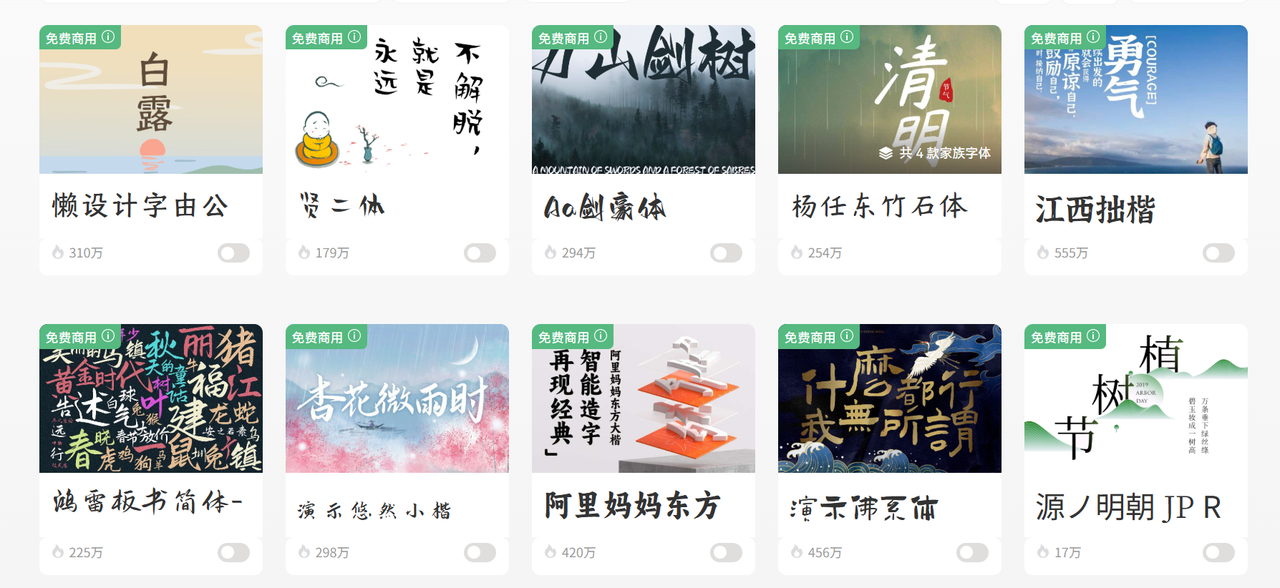
免费商用的古风字体下载网站推荐:6个靠谱平台实测分享(2026)
字由:我最常用的字体管理工具
字由 是我电脑上必装的软件,不仅仅是个下载平台,更是个字体管理神器。
在字由的字体库里,我筛选"免费商用"标签,能看到不少古风字体。比如Aa剑豪体、江西拙楷、贤二体这些,都是可以免费商用的。字由会在字体详情页清楚标注授权范围,哪些场景可以用,哪些不行,都写得很明白。
我在字由里收藏了十几款古风字体,做项目时直接搜索关键词"书法""古风""楷体",预览效果后激活使用。字由还支持字体对比功能,可以同时预览多款字体在同一段文字上的效果,选择起来特别直观。
猫啃网
猫啃网是我发现的一个专注免费商用字体的分享站。站长把网上能找到的免费商用字体都整理了出来,分类很清楚,有专门的"书法字体"栏目。
我在猫啃网下载过江西拙楷、霞鹜文楷、汉仪文黑这些字体,都是完全免费商用的。网站对每款字体都附上了授权说明链接,可以追溯到官方声明,用起来很安心。
猫啃网的界面比较朴素,没有太多花哨功能,但胜在资源全、更新快。如果你想一次性找到很多免费古风字体,这里是个好去处。有些字体在其他平台不好找,猫啃网都给整理好了。
100font
100font 主打的是精品免费商用字体收集。网站设计得比较清爽,字体数量不算特别多,但每一款都是精选过的。
我在这里找到了文泉驿正黑、思源宋体、装甲明朝等字体。其中思源宋体是 Adobe 和 Google 联合开发的开源字体,字重选择丰富,从细到粗有七个级别,用在古风设计里做标题或正文都很合适。
字体天下
字体天下 是个老牌字体下载站,资源库非常庞大。不过要注意,这里不是所有字体都免费商用,一定要筛选"免费字体"分类。
站酷字库
站酷是设计师社区,他们推出了几款完全开源免费商用的字体,包括站酷高端黑、站酷快乐体、站酷文艺体、站酷小薇logo体等。
虽然站酷的字体数量不多,但质量都不错。其中站酷快乐体带点手写感,用在一些轻松活泼的中国风设计里挺合适的。我之前做过一个新年海报,用站酷快乐体写"福"字,感觉比严肃的楷书多了点亲和力。
Google Fonts
Google Fonts 是国际知名的开源字体平台。对于中文古风字体来说,这里最值得关注的是思源字体系列(Noto 系列和 Source Han 系列)。
思源宋体是我做古风设计时的常客。它有简体中文、繁体中文、日文、韩文多个版本,笔画设计兼顾传统宋体的特点和现代阅读需求,用在书籍排版、文章配图、海报标题都很合适。
写在最后
免费商用的古风字体资源虽然不如收费字体丰富,但只要用心找,还是能满足大部分项目需求的。我现在电脑里常备十几款免费古风字体,从楷书、宋体到书法体都有,基本覆盖了日常设计场景。